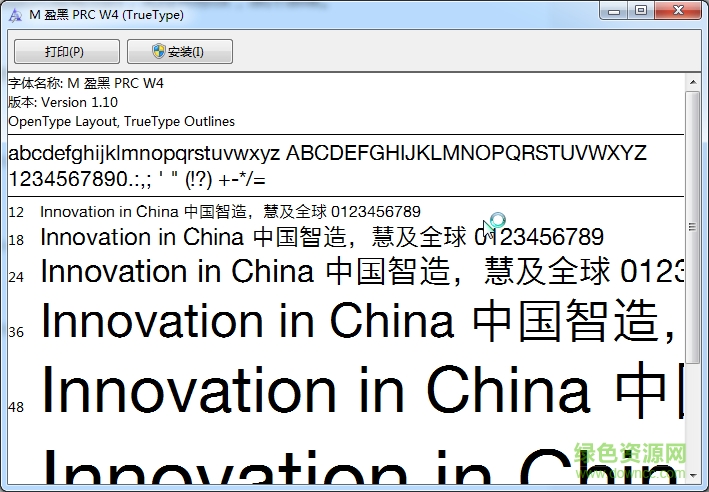
盈黑字體全稱m 盈黑 prc字體,包括w2、w3、w4、w5、w7、w8六款字體,每款都有著不同深淺和粗細(xì)度,常出現(xiàn)在正規(guī)圖文的使用中,嚴(yán)謹(jǐn)大方,喜歡的就來(lái)綠色資源網(wǎng)下載吧!
m 盈黑 prc字體包括:M 盈黑 PRC、M 盈黑 PRC W2、M 盈黑 PRC W3、M 盈黑 PRC W4、M 盈黑 PRC W5、M 盈黑 PRC W7、M 盈黑 PRC W8、MYingHeiPRCW48等,是蒙納字體黑體的全新升級(jí)!
蒙納黑體的五組粗細(xì),特別為印刷機(jī)和不同紙張的印刷效果而訂定。它從以往照相排字機(jī)專用字型走到今天的數(shù)碼印刷,到最近十年流動(dòng)配置、平板電腦的冒起,蒙納黑體面對(duì)的挑戰(zhàn)一天比一天多。所以,蒙納公司決定開(kāi)發(fā)一套全新的黑體,無(wú)論在今天顯示細(xì)膩無(wú)瑕、達(dá)至 5K / 視網(wǎng)膜屏 (Retina Display) 素質(zhì)的屏幕還是手機(jī) app 上的文字,要達(dá)致像蒙納黑體在印刷上的水平。畢竟紙面是依靠光線反射而造成閱讀效果,相反手機(jī)、平板電腦屏幕則依靠屏幕像素顆粒跟背光構(gòu)成影像顯示,所以必須有不同的解決方案應(yīng)付這一波新趨勢(shì)。